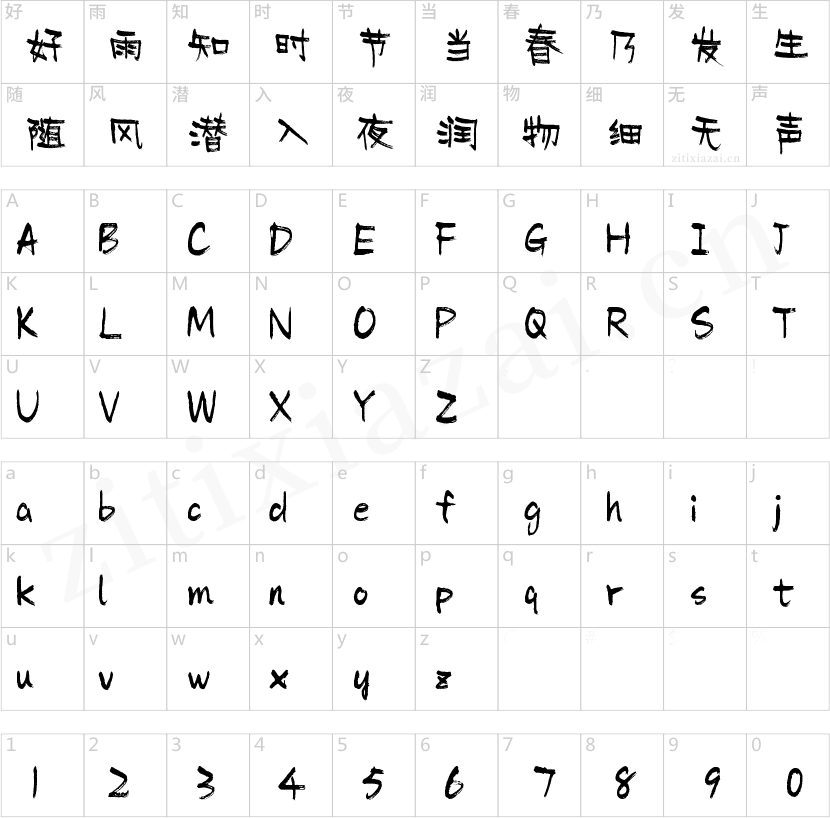
字魂133号-墨客枯笔
字魂133号-墨客枯笔,这款字体结构工整、笔画清晰,兼顾美观与易读性,适用于标题、正文、海报、包装、LOGO 等多种场景。字形优雅稳定,风格百搭耐看,适配日常排版与创意设计,让文字呈现更舒适、更具质感。字魂133号-墨客枯笔一笔一画,皆是细节,以均衡的比例、流畅的线条打造舒适视觉体验,字形端正大气,风格简约现代。无论是商业设计、品牌宣传还是日常排版,都能轻松驾驭,让文字更有格调与力量。字魂133号-墨客枯笔字体下载。
字魂字体字小魂墨客枯笔字体是由字魂创意字库设计并生产的一款可商用的字体,被收录于字小魂系列。该字体支持GB-2312标准,包含6764个中文、字母、符号和数字,字体类型偏向毛笔书法,具有中国风、简约、时尚、帅气的风格,在市面上广泛用于公益宣传、企业文化、海报企宣等场景。